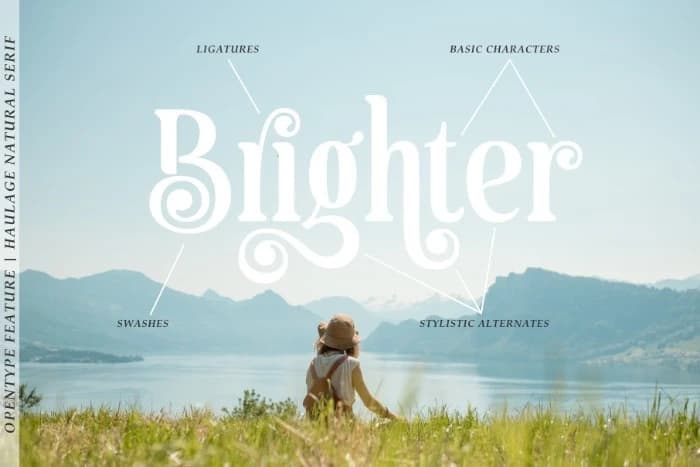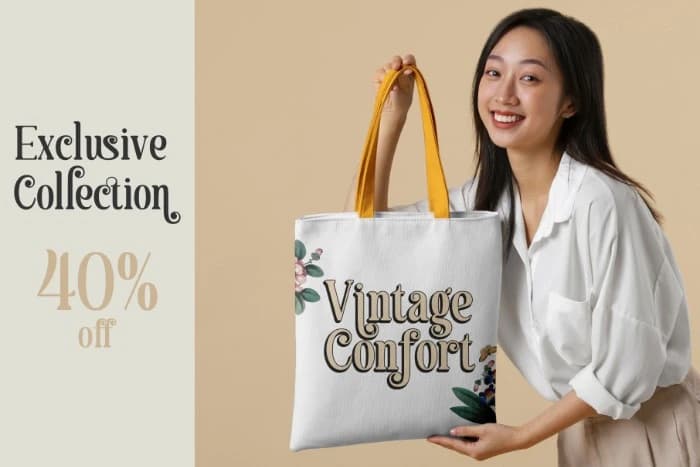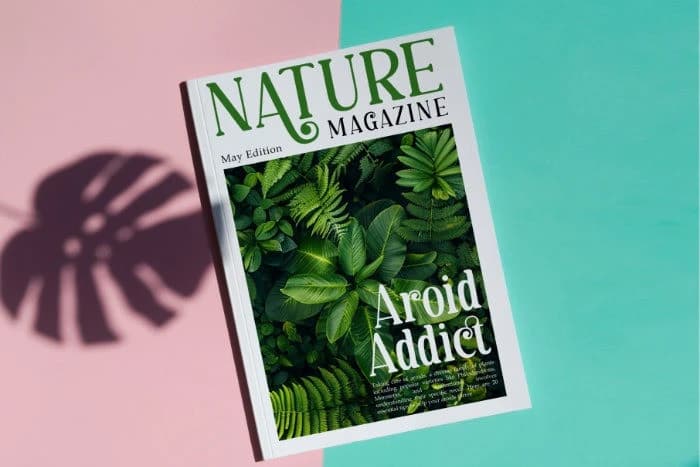
Haulage Yazı Tipi
Haulage Font, zamansız zarafet ve çekiciliği yansıtan doğal, el yapımı bir serif yazı tipidir. Detaylara titizlikle özen gösterilerek tasarlandı ve Haulage Font, özellikle ligatürlerinde ve alternatiflerinde benzersiz, doğal ve klasik karakterlerin çeşitliliğine sahiptir.
Haulage Font, doğal el yapımı bir serif yazı tipi olup zamansız zarafet ve çekicilik yayıyor. Ayrıntılara titizlikle özen gösterilerek tasarlanan Haulage, özellikle ligatürlerinde ve alternatiflerinde benzersiz, doğal ve klasik karakterlerin çeşitliliğine sahiptir.
Haulage